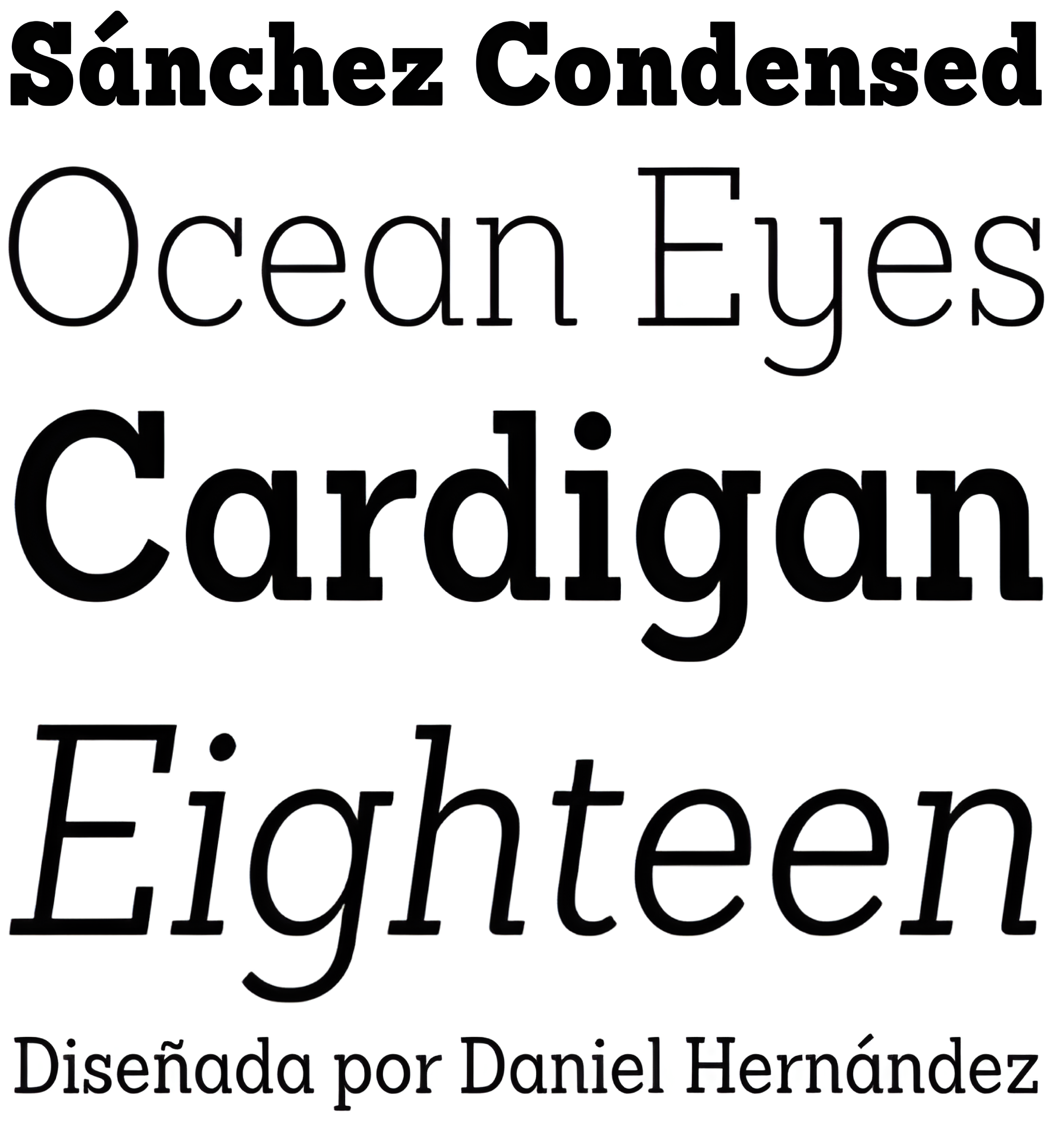
| Descripción | Sánchez, diseñado por Daniel Hernández, es un tipo de letra con gracias perteneciente a la clasificación slab serif, o egipcio, que guarda un gran parecido con el icónico Rockwell, pero con los bordes redondeados, lo que ofrece contraste y equilibrio a la estructura cuadrada. Sánchez & Sánchez Condensado consta de 12 variantes, que van de la extra clara a la negra, cada una con la misma altura x. Las variantes normal y cursiva están disponibles gratuitamente. |
| Familia(s) | ExtraLight, ExtraLight Italic, Light, Light Italic, Regular, Italic, SemiBold, SemiBold Italic, Bold, Bold Italic, Black, Black Italic |
| Estilos | 12 |